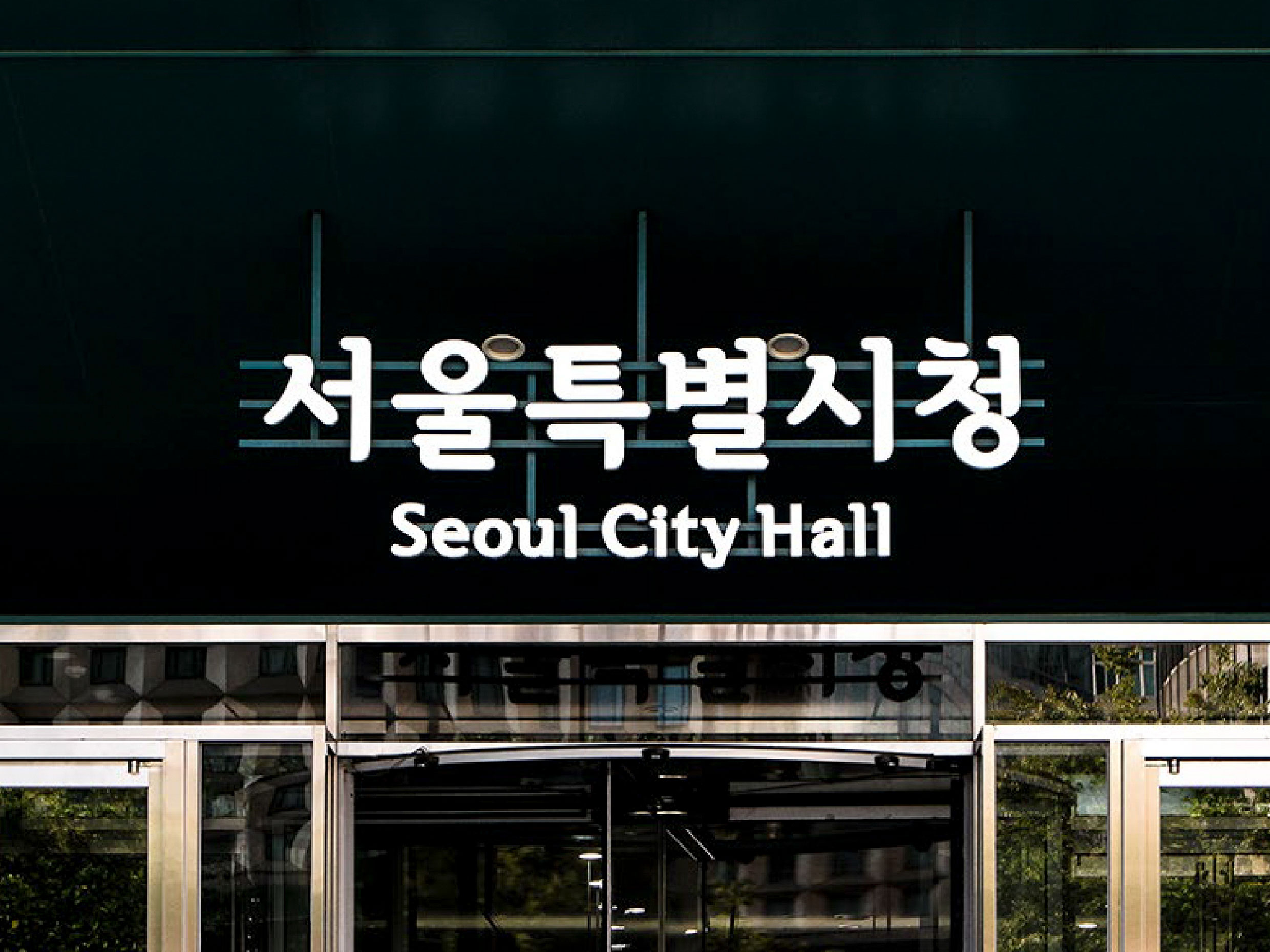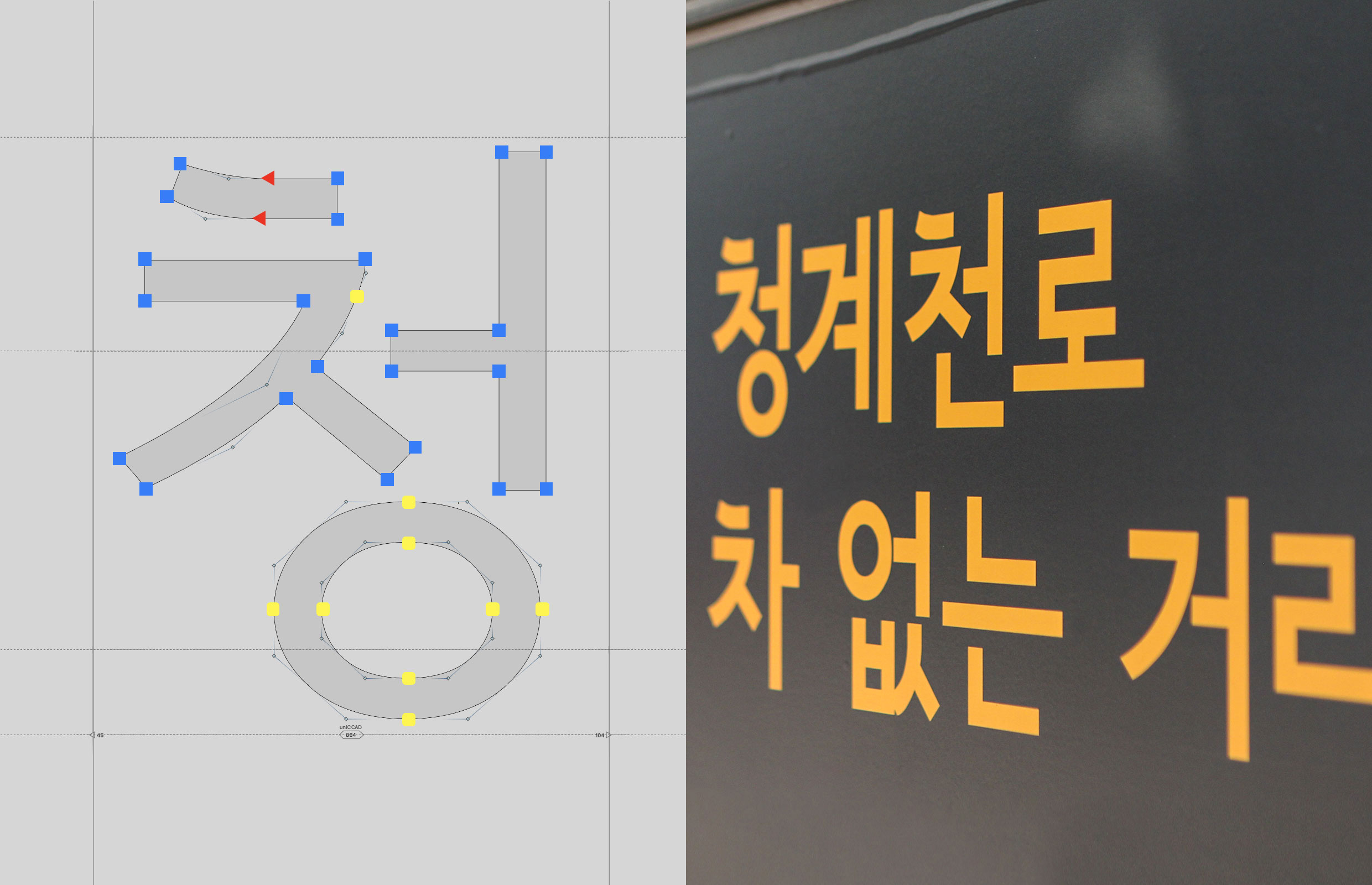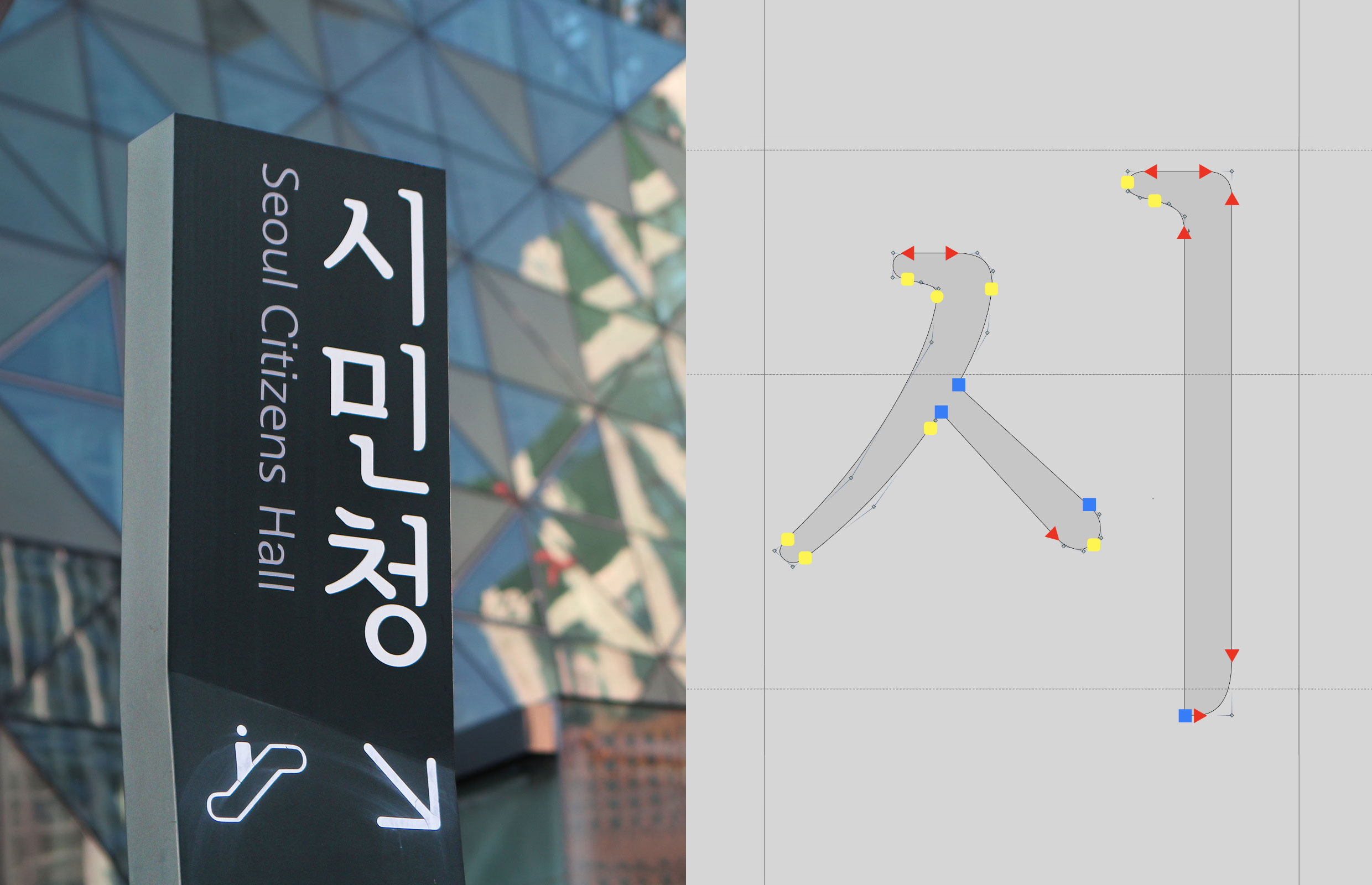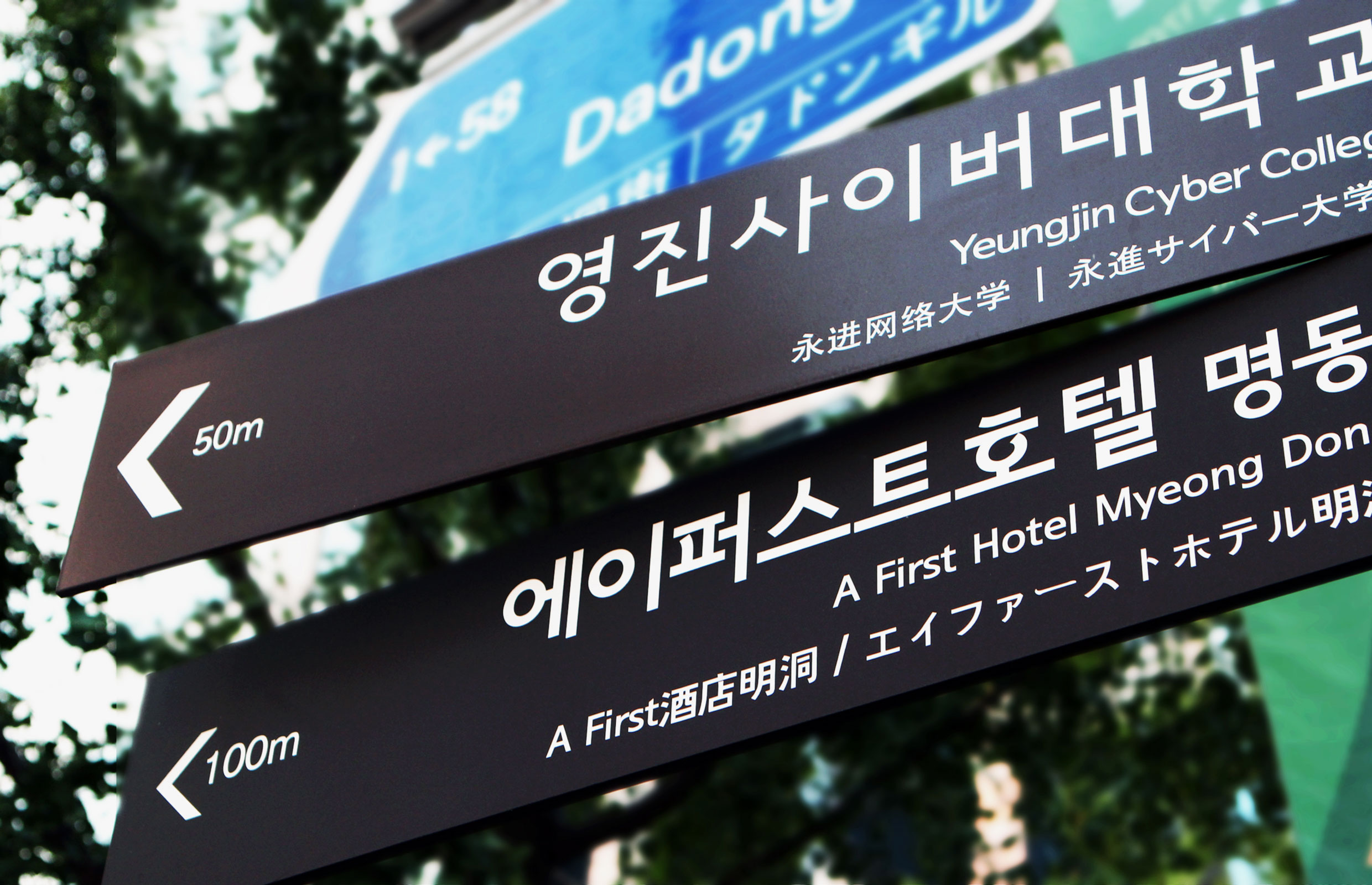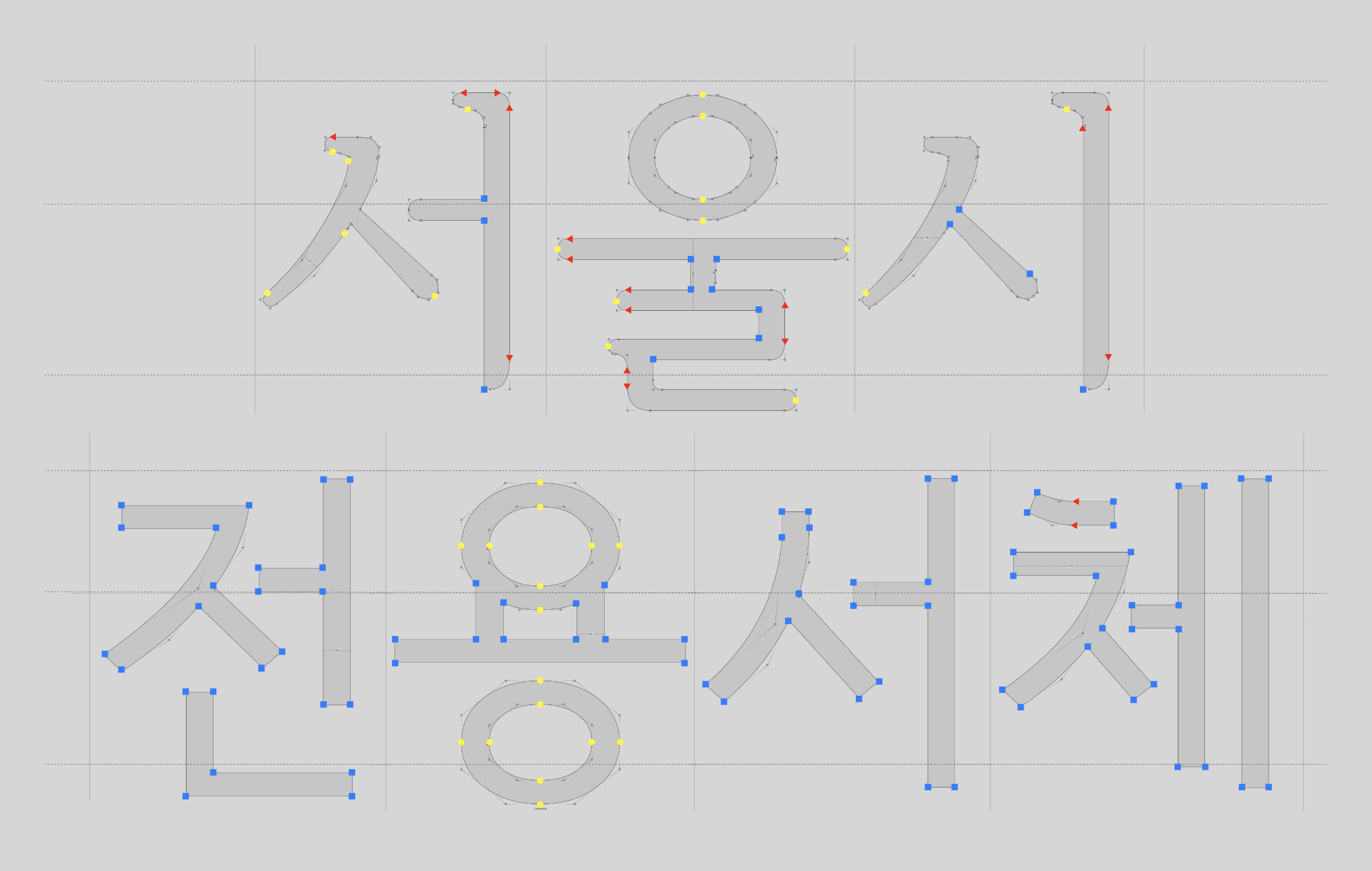
서울시 [서울한강체, 서울남산체]
서울서체는 서울이 가진 역사성, 전통성, 문화성, 사회성 등의 심층적 고찰을 바탕으로 하여 세련되고 소프트한 현대적 감성을 담아냈다. 단순한 구조와 간결한 형태는 여유로운 멋과 편안함을 보여주며, 서울한강체와 서울남산체는 동일한 골격을 가짐으로써 진정한 서체 가족군을 형성했다.